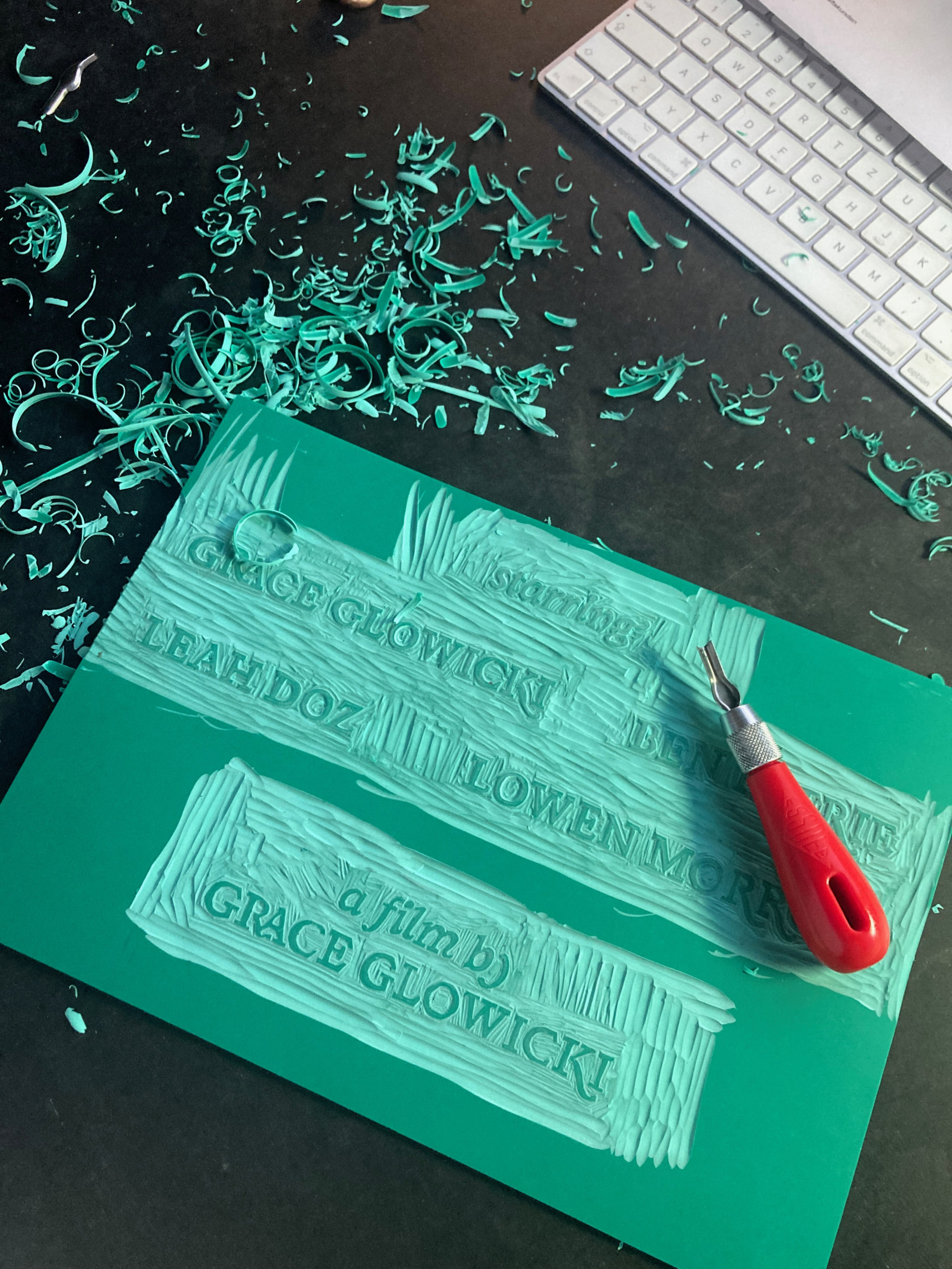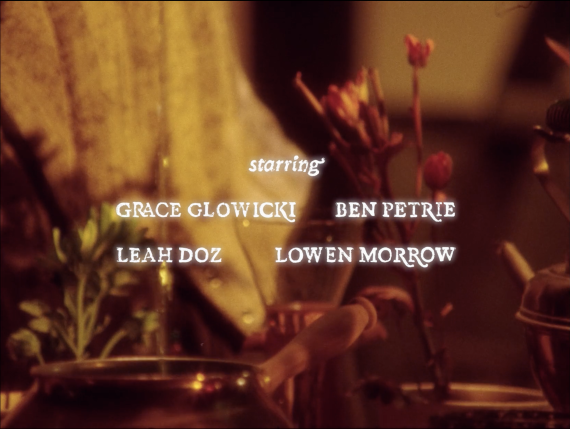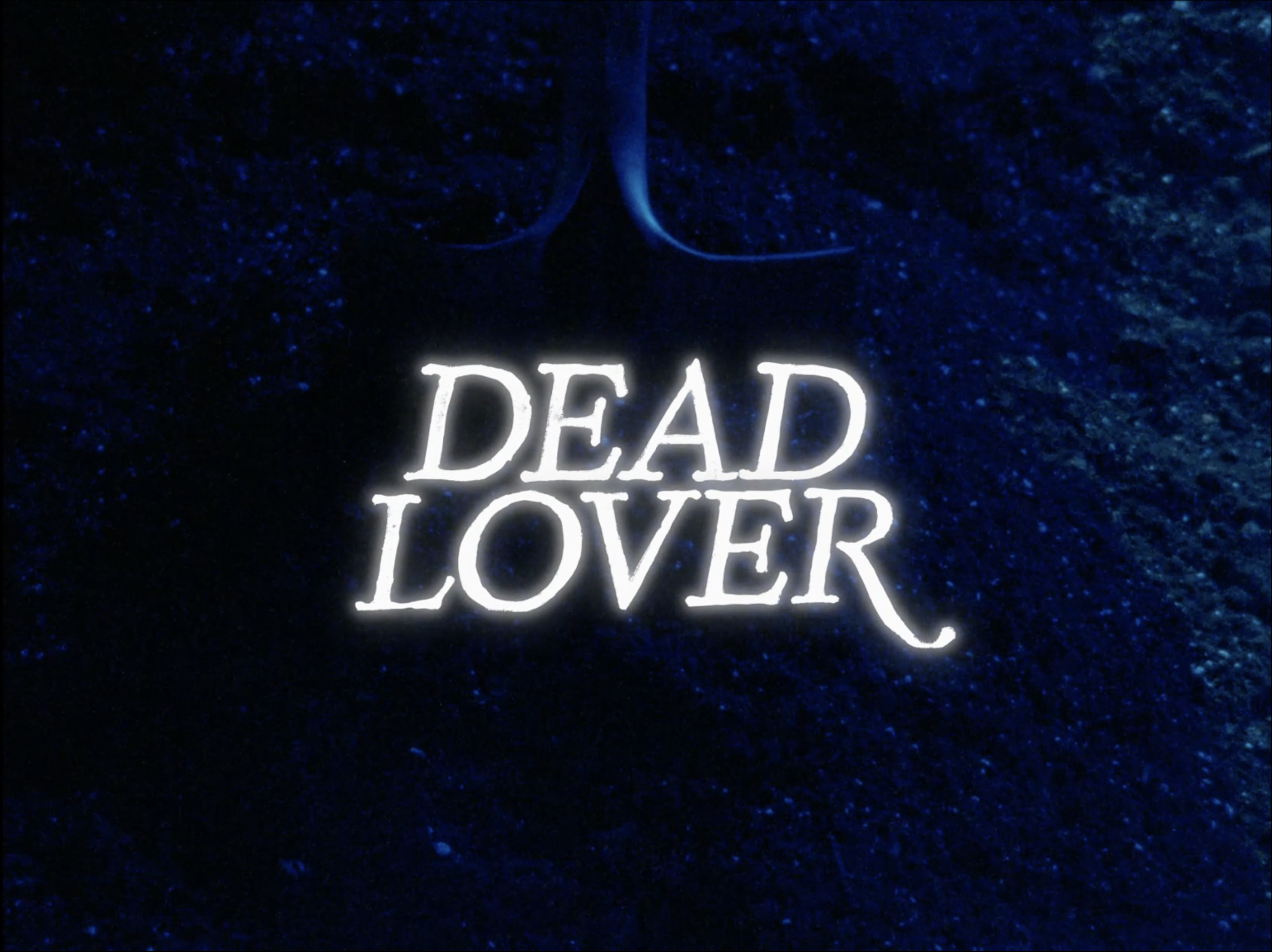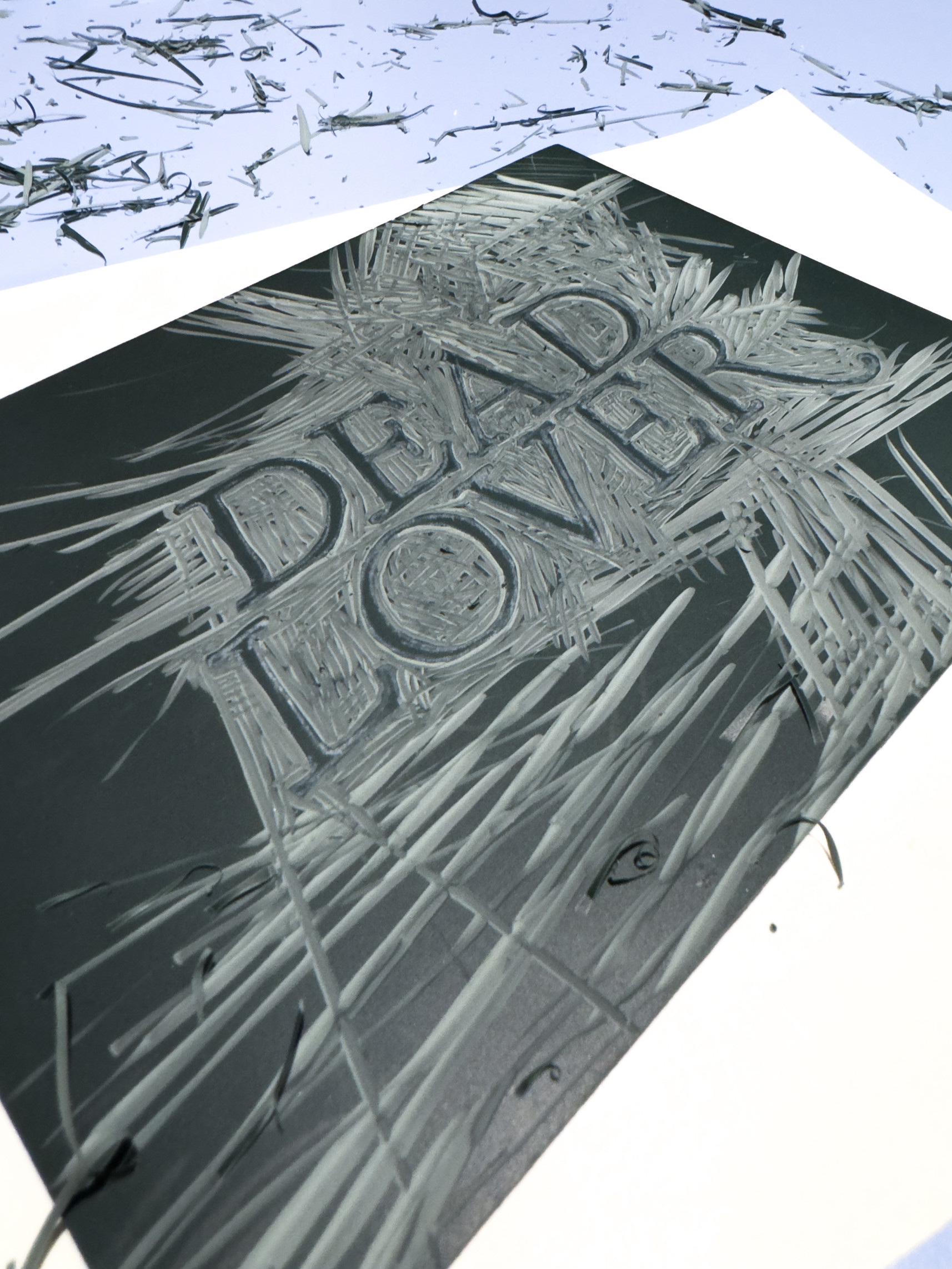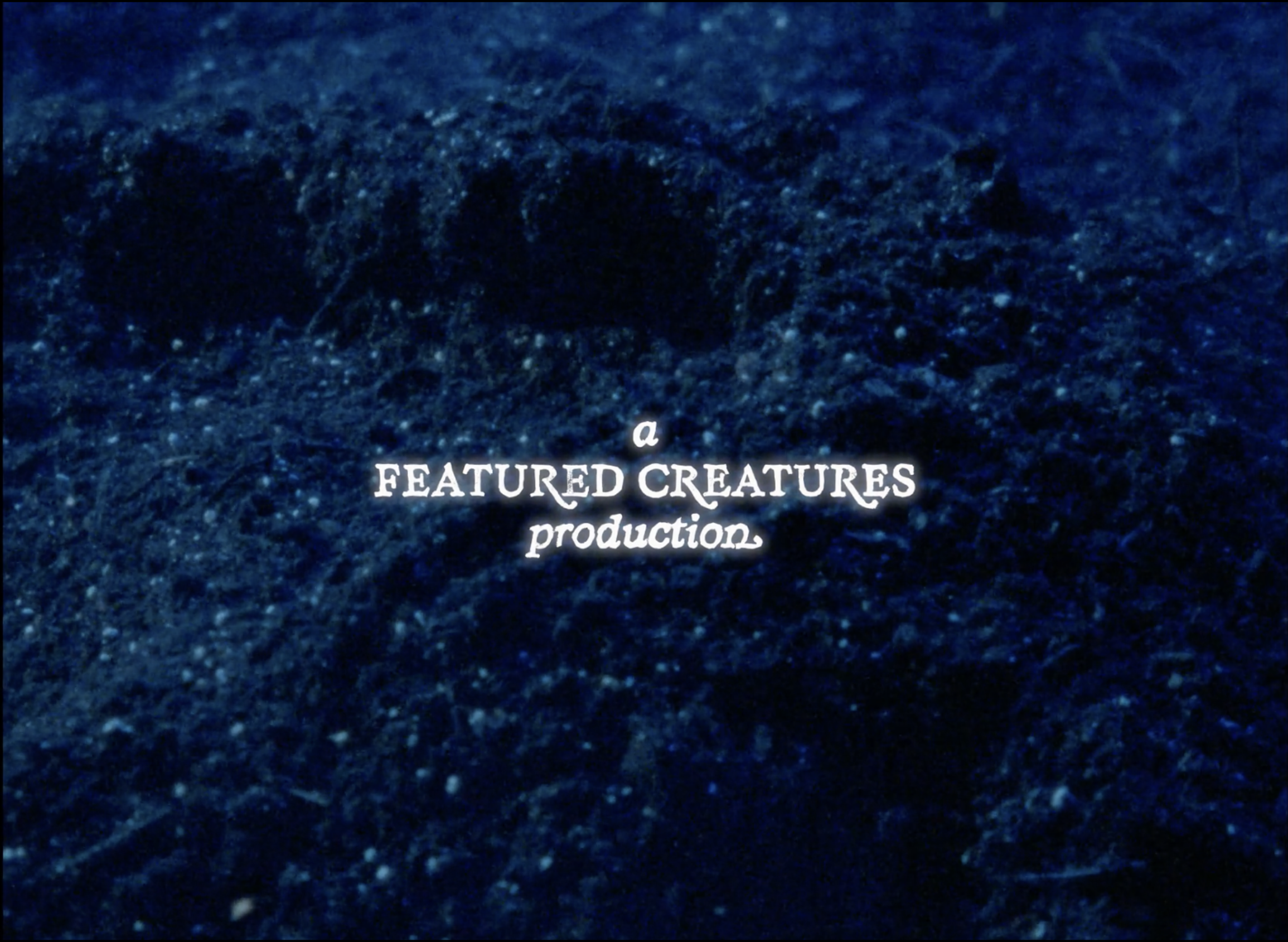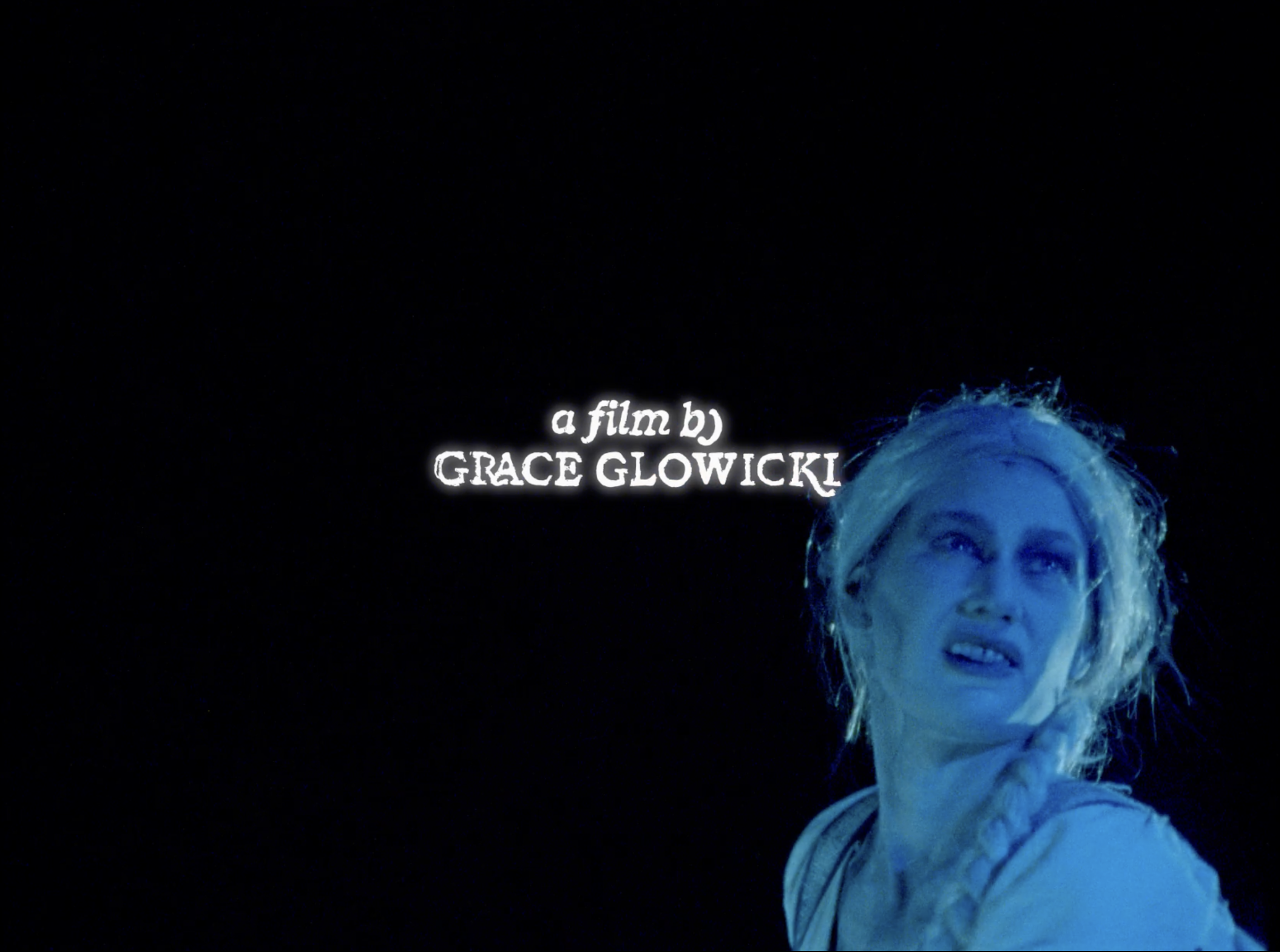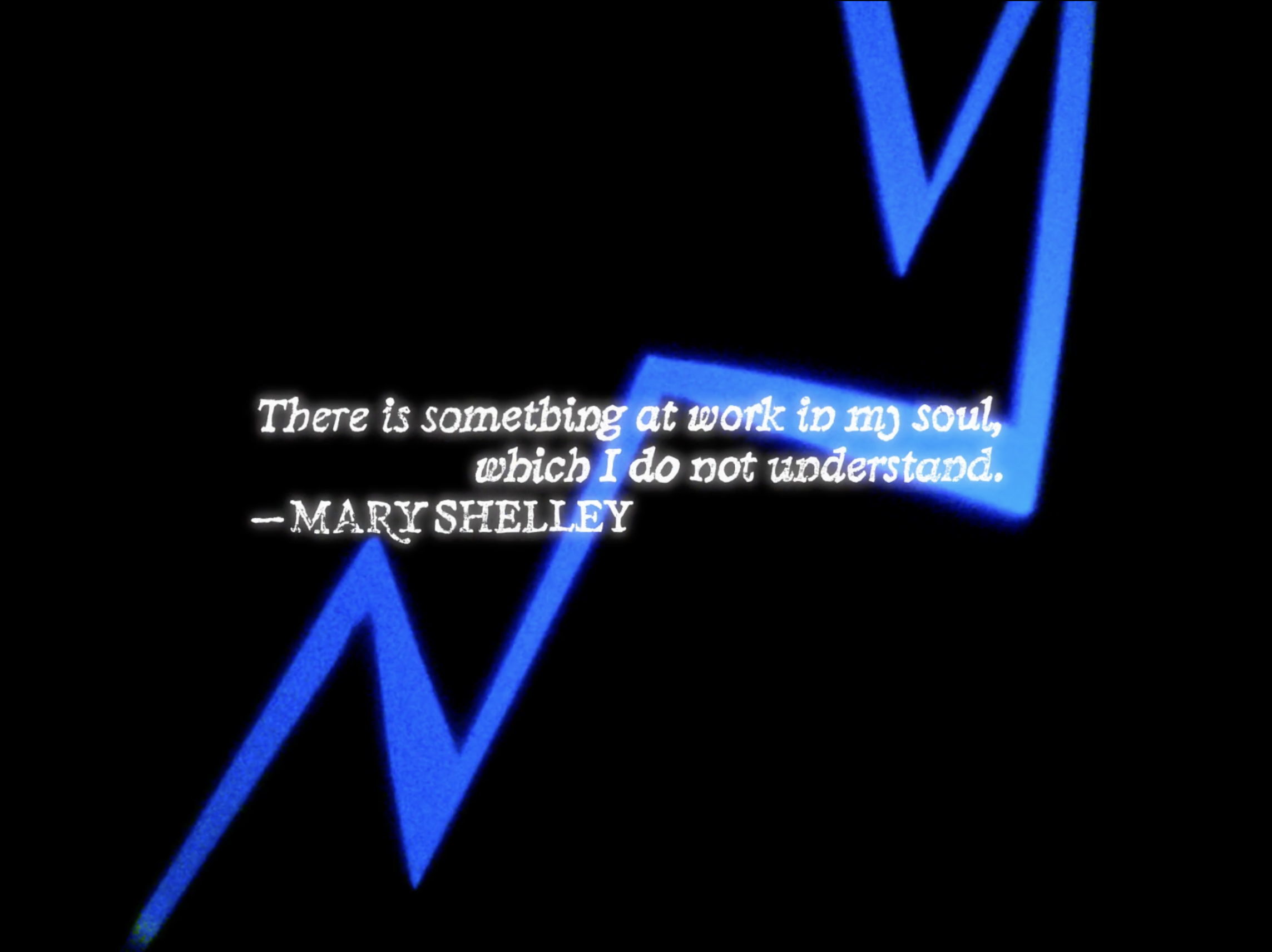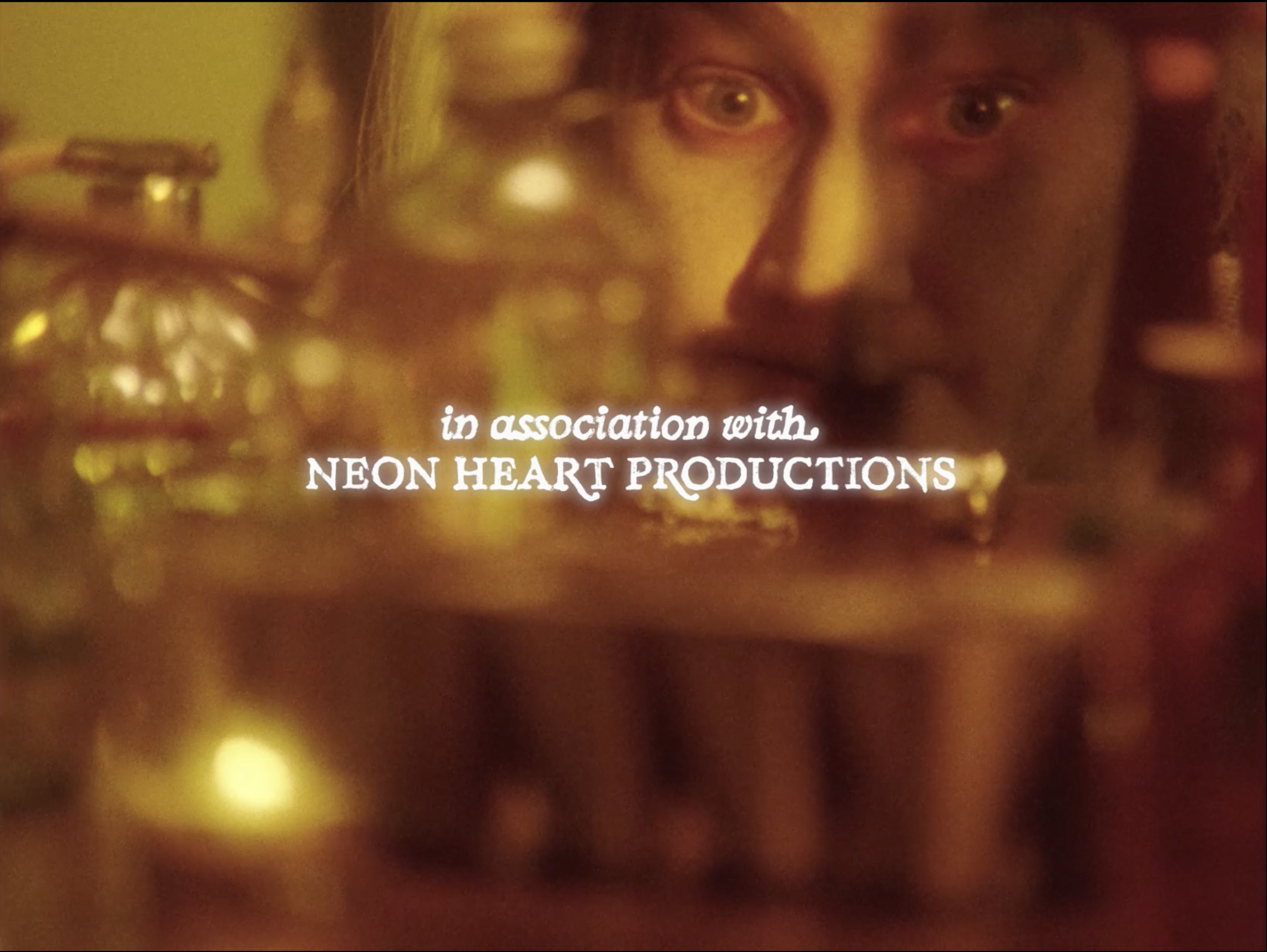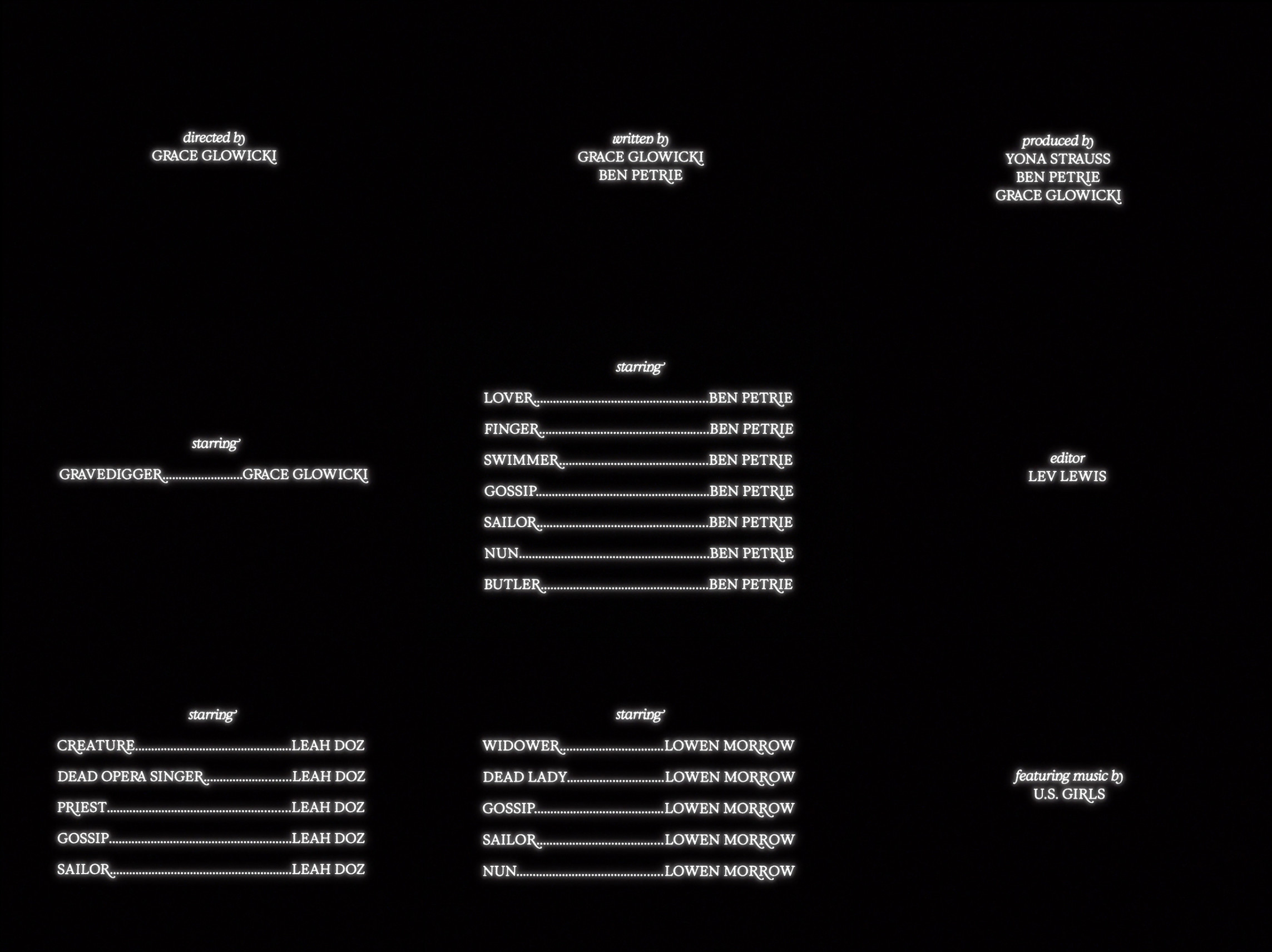
Dead Lover
Dead Lover ist ein kanadischer Thriller von Grace Glowick. Inspiriert von Mary Shelleys Frankenstein verfolgt der Film den Versuch einer Totengräberin, ihren verstorbenen Liebhaber wiederzubeleben.
Die Titel wurden im Linolschnittverfahren gedruckt und wieder eingescannt, um ihnen einen handgemachten Charakter zu verleihen und so der DIY- und experimentellen Theaterästhetik des Films gerecht zu werden. Die langen Abstriche der Buchstaben der Schriftart Kalice spielen auf den immer länger werdenden abgetrennten Finger des Geliebten im Film an.
Schrift: Kalice von Margot Lévêque